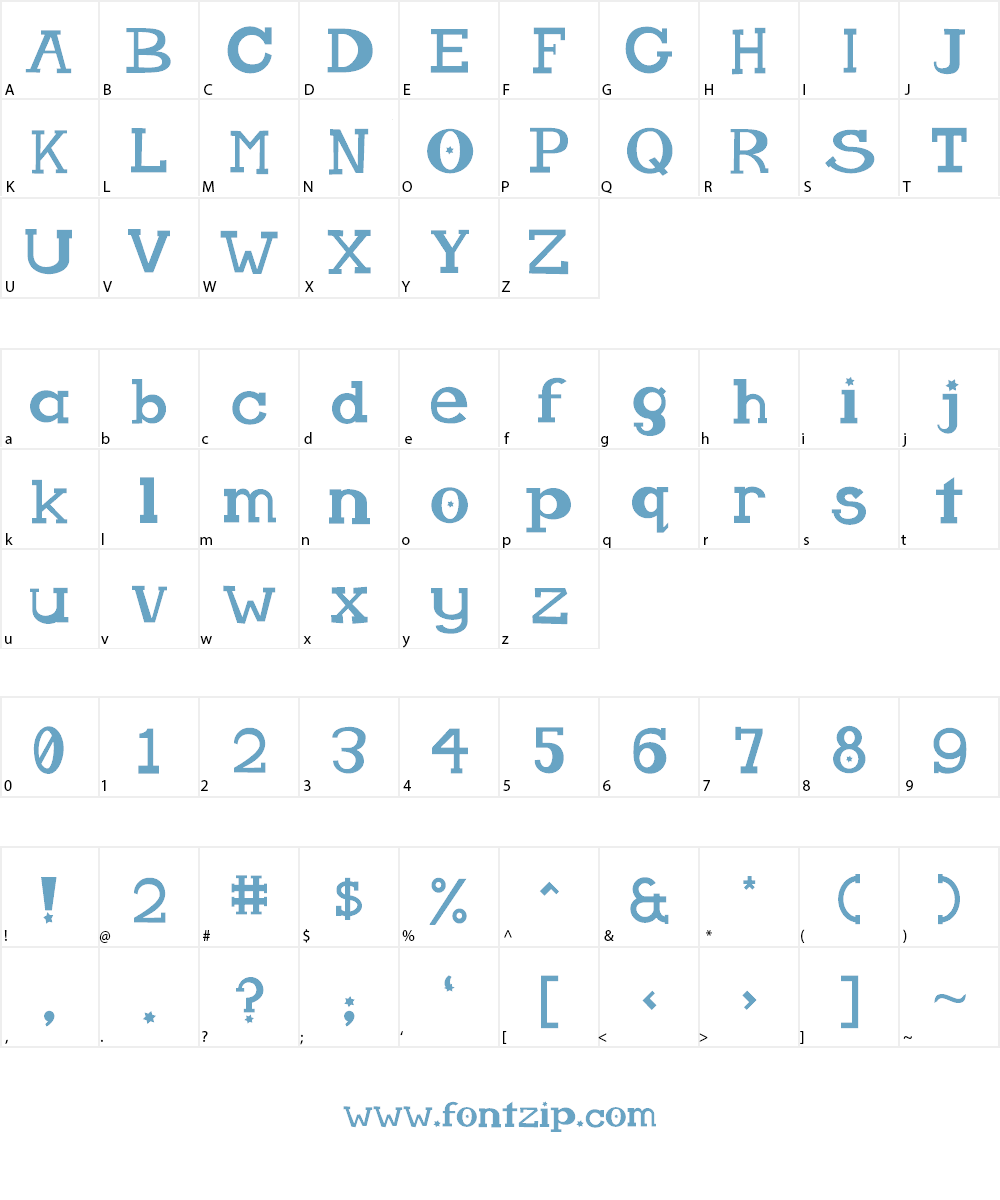
Stellalumina est une police qui souhaite un assistant.
Ceci emprunte et le modifie à partir de la police Merriweather Sans(https://www.fontspace.com/sorkin-type/merriweather-sans ) par Sorkin Type.